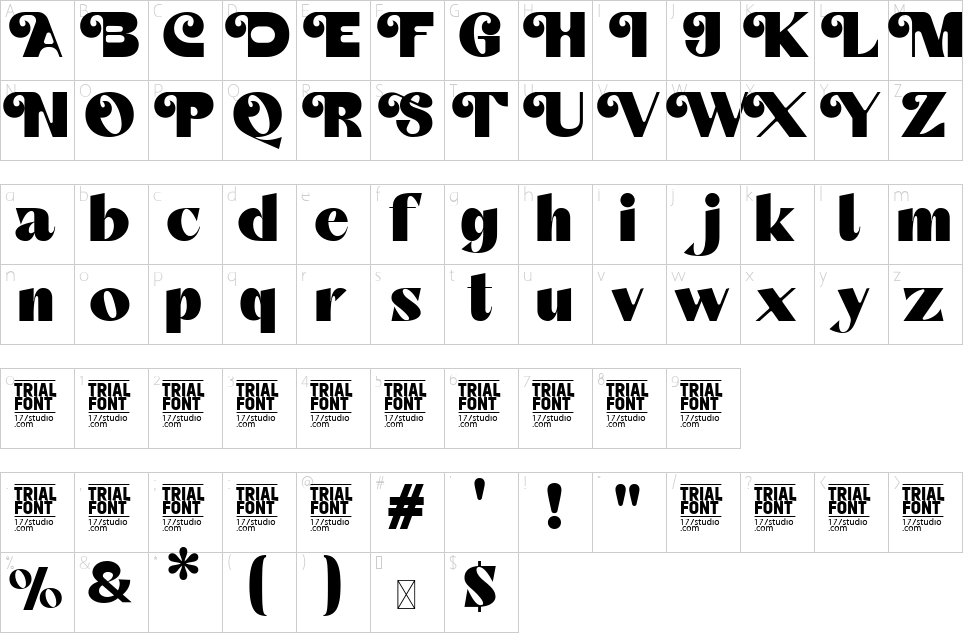
A fonte ‘Manifest Creativity’ é uma opção gratuita e versátil para quem busca uma experiência gráfica interessante e atraente. Desenvolvida pelo 177studio.com, essa fonte foi projetada para oferecer uma variedade de opções em estilos diferentes, adequada para diversos projetos de design. Se você está procurando por uma fonte que seja tanto versátil quanto fácil de usar, ‘Manifest Creativity’ é uma boa escolha. Com uma instalação rápida e fácil, a fonte pode ser aplicada tanto em ambientes Windows quanto em Mac, permitindo uma variedade de possibilidades de criação. O fato de ser gratuita faz dela ainda mais atraente para designers que buscam economizar sem sacrificar qualidade. Com uma versão gratuita, você pode experimentar o design e o visual que ela pode oferecer antes de considerar qualquer compra.